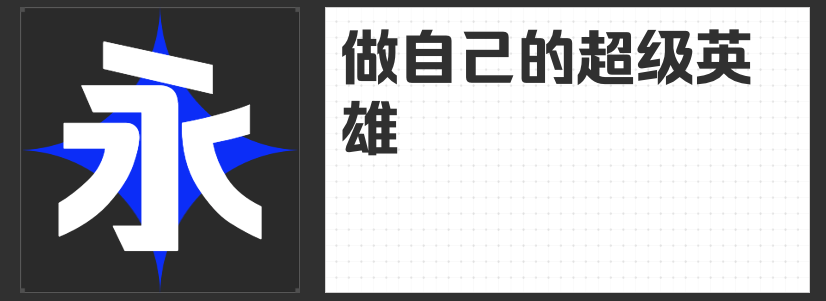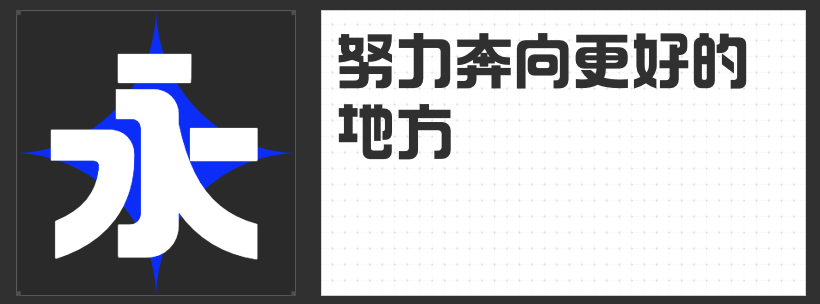
四款设计力作:解锁视觉表达的多元美学语言
在当代设计中,字体的选择不仅是信息传递的载体,更是品牌调性与情感共鸣的视觉触点。本文精选四款兼具艺术张力与实用价值的商业字体,从几何解构到传统新生,从力量感营造到优雅重塑,为设计师提供突破常规的创意工具。
1. 造字侠地铁修悦体 特粗
以胶带拼贴为灵感来源,这款字体通过方正的模块化结构与平直切口,构建出充满手工感的几何美学。笔画间刻意保留的不规律留白与重心偏移,打破了传统字体的静态平衡,赋予排版动态的呼吸感。其特粗字重进一步强化了视觉冲击力,使文字本身成为画面中的图形元素,适合需要制造记忆点的标题设计或品牌视觉标识。
2. 造字侠热辣隶简
这款字体以隶书为基因,通过扁宽中宫与开张横笔重构古典骨架,同时以简洁线条与自然过渡的笔画粗细,消解传统隶书的厚重感。撇捺的舒展与竖钩的直线概括,形成刚柔并济的视觉节奏,既保留历史文脉的庄重感,又契合当代国潮设计对“新中式”美学的追求,适用于需要文化厚度与现代感平衡的场景。
3. 励字造梦简 特粗
灵感源自城市天际线的摩天大厦,这款字体以不对称结构模拟建筑透视——左侧倾斜的笔画与右侧竖直线条形成张力,仿佛文字在空间中延伸生长。特粗字重与棱角分明的轮廓强化了力量感,而直线构成的几何形态则暗含理性秩序,适合科技、运动或青年文化领域,传递突破常规的创造精神。
4. 励字超级勇士简 特粗
作为对经典黑体的创新诠释,这款字体通过圆弧转折替代生硬直角,在保持现代简约风格的同时,注入柔和的视觉温度。优化后的笔画比例使字体更轻盈易读,特粗字重则确保了远距离识别的清晰度,适用于需要兼顾专业感与亲和力的品牌传播场景,如高端零售、公共服务或数字界面设计。
这四款字体以独特的造型语言与文化内涵,为设计注入超越功能的美学价值。无论是追求个性表达的品牌,还是需要差异化视觉的内容创作者,都能从中找到激发灵感的解决方案。